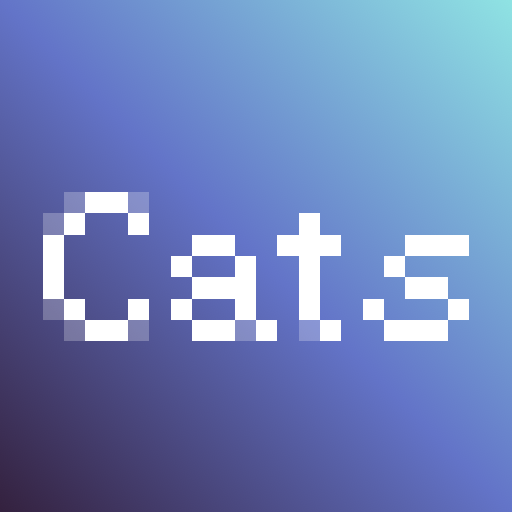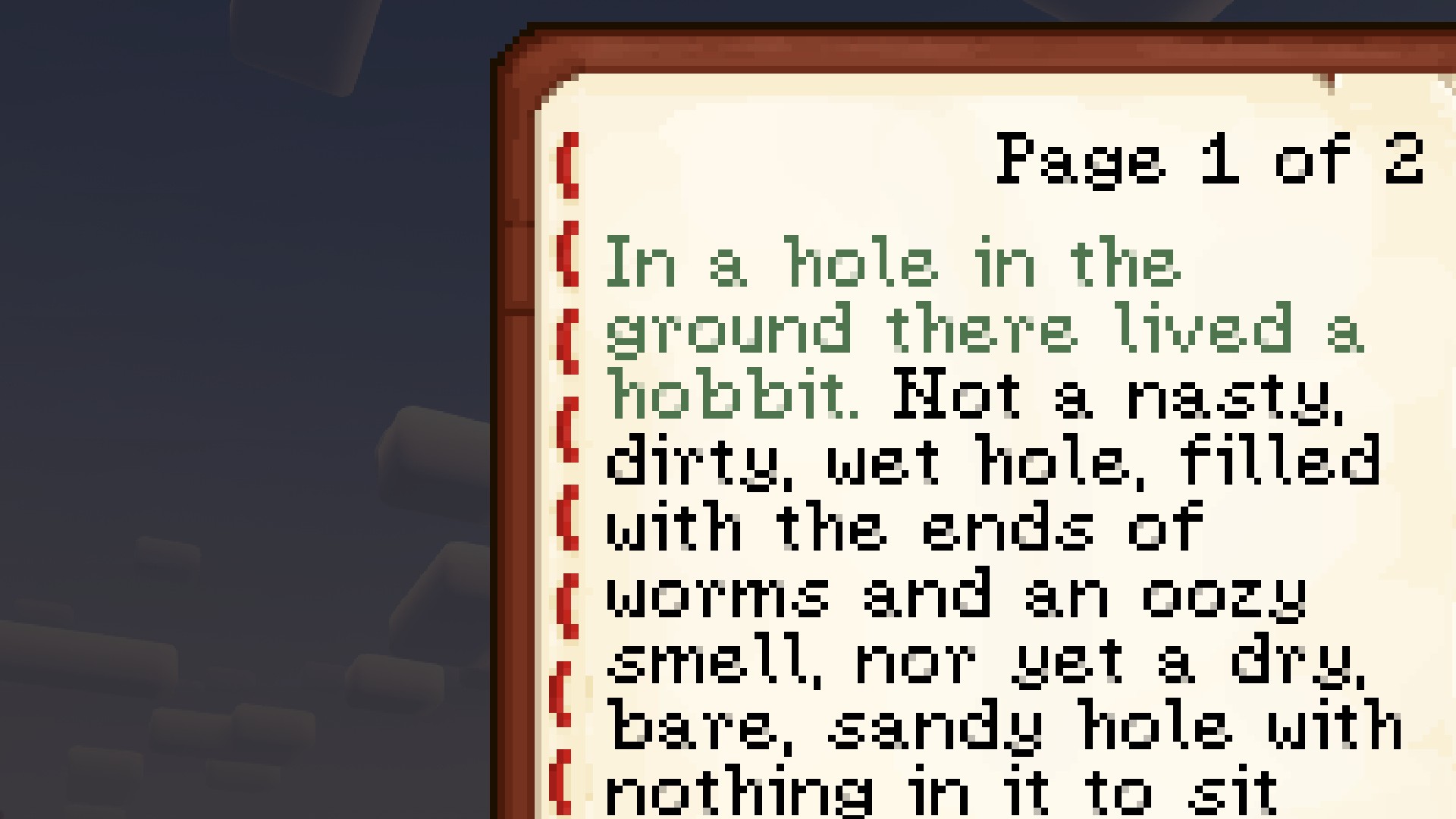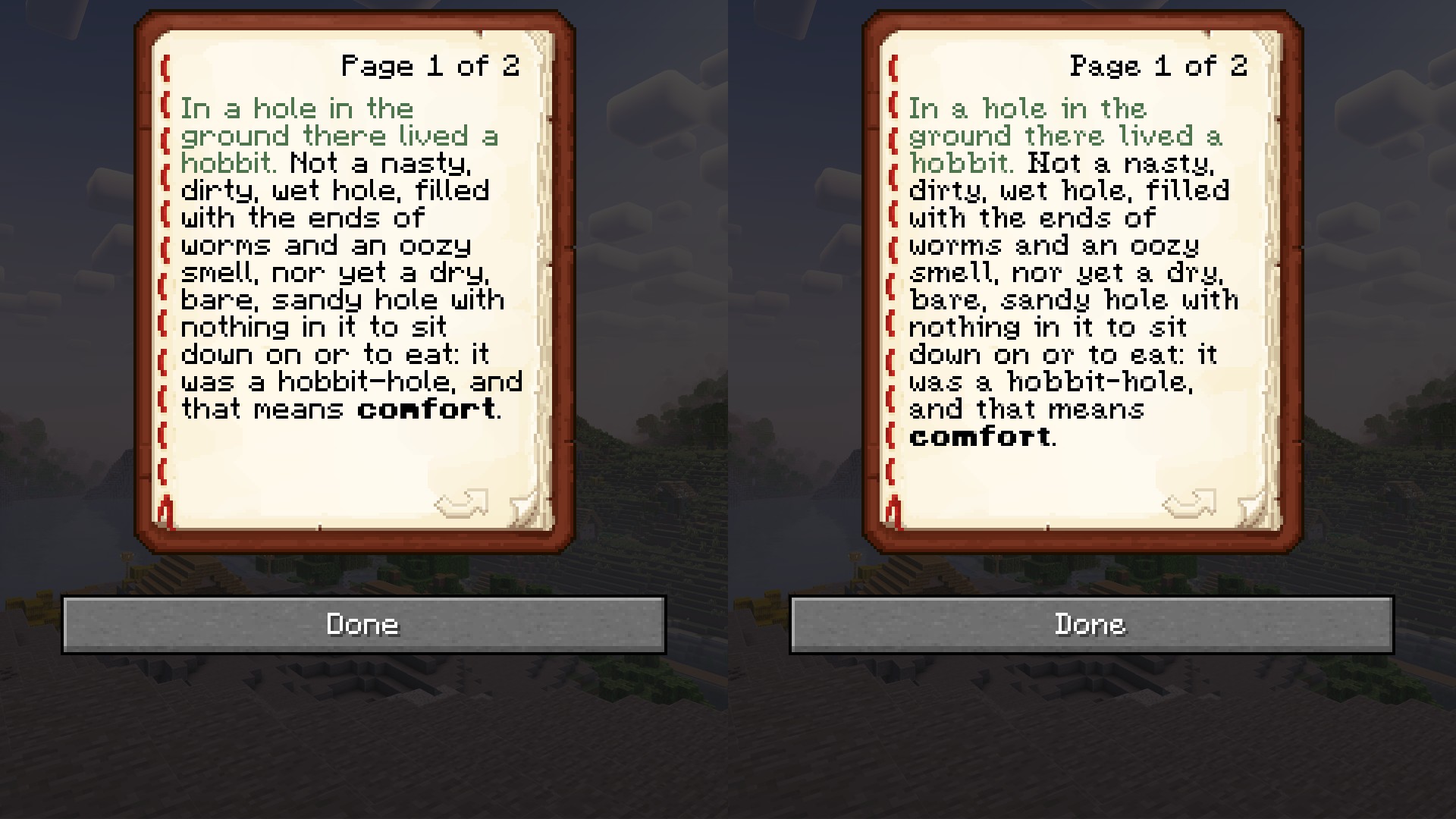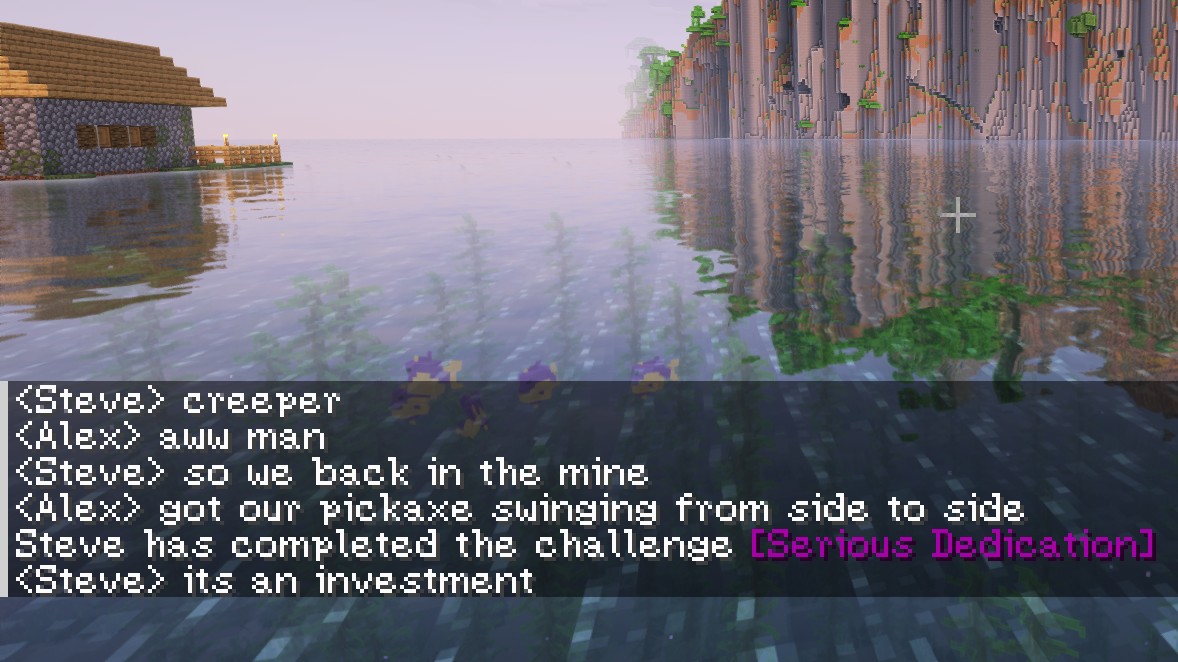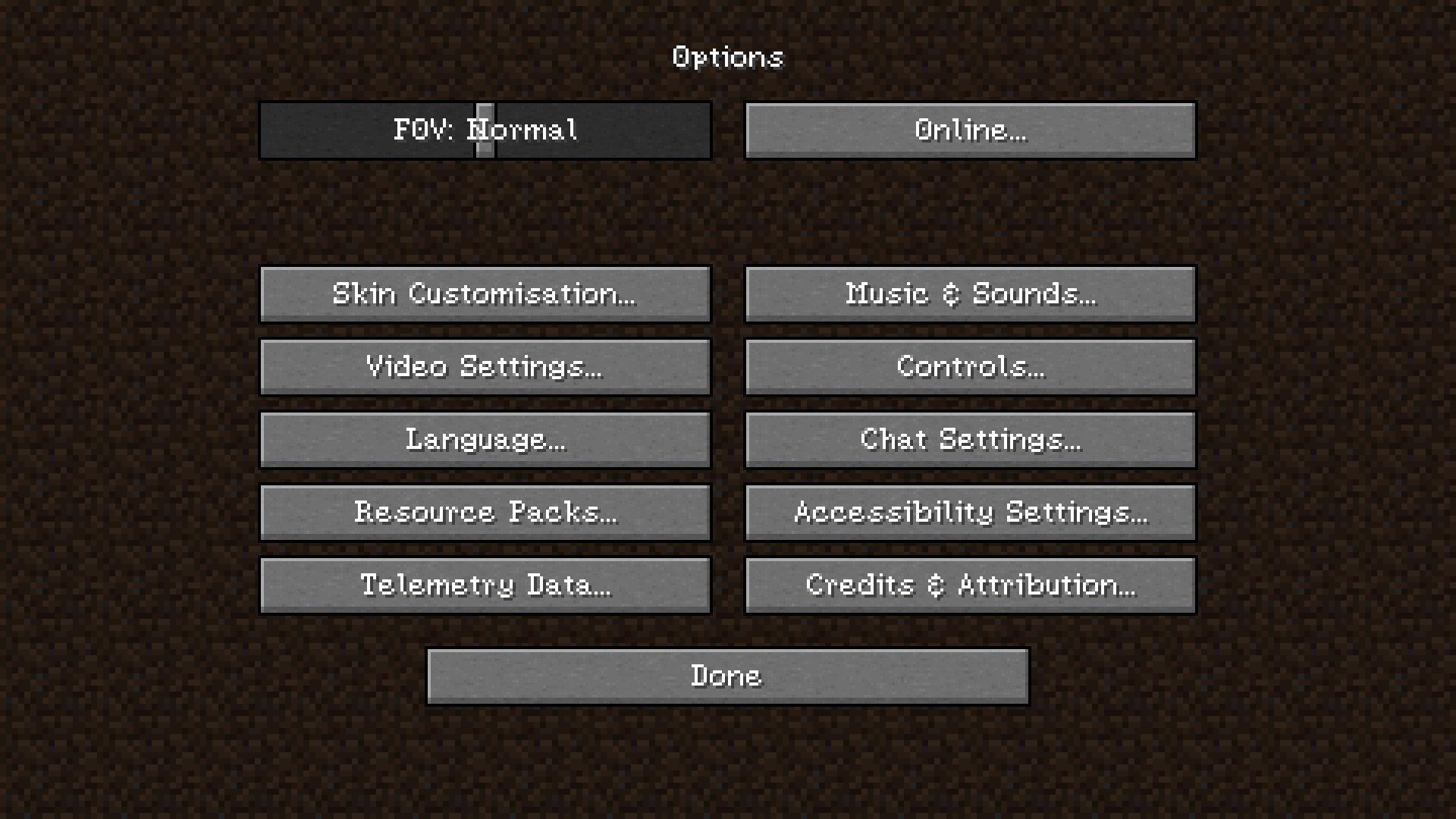
(Bee's) Serified Font
Уникальный ресурс-пак преобразует шрифт в фэнтезийном стиле.
Описание мода
Мод (Bees) Serified Font — это уникальный ресурс-пак, который полностью перерабатывает шрифт в Minecraft. Его основная цель — создать текст, который отражает фэнтезийную атмосферу и магическую средневековую эстетику игры. Этот мод не только придаёт шрифту более человечный и читаемый вид, но и использует семи-прозрачные пиксели для сглаживания, что делает текст ещё более привлекательным на экране.
Особенности мода
• Фэнтезийный дизайн: Новый шрифт лучше соответствует стилистике игры и добавляет атмосферы.
• Читаемость: Сделано всё для того, чтобы тексты были максимально удобочитаемыми.
• Сглаживание: Использование полупрозрачных пикселей значительно улучшает внешний вид текста.
• Не поддерживает диакритические знаки: В планах расширение функционала, чтобы добавить поддержку акцентов и диакритики.